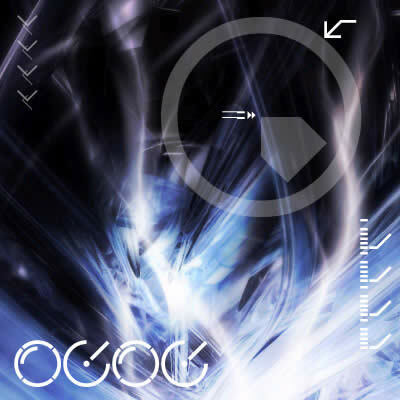
Style Bats autorstwa Vinterstille to darmowy geometryczny font typu dingbats o ostrym, „wczesno-cyfrowym” charakterze. Zestaw opiera się na przejrzystych symbolach – diamentach, chevronach, paskach, schodkowych zygzakach i celownikach w ramkach – powtarzanych w surowym, modułowym rytmie, który przywodzi na myśl połączenie oznaczeń graficznych, ikon interfejsu i abstrakcyjnych ornamentów.
Ten darmowy font sprawdzi się wszędzie tam, gdzie projekt wymaga kompaktowych akcentów graficznych: w plakatach, oznaczeniach sekcji w magazynach, grafikach albumów, kartach tytułowych, projektach opakowań czy prostych nagłówkach stron www. Dzięki temu, że motywy są oszczędne i przypominają wzory, font świetnie sprawdza się w roli obramowań, separatorów, wypunktowań i krótkich znaków graficznych, gdzie zaledwie kilka symboli wystarczy, by przekazać cały zamysł wizualny.
Ostatnio dostrzeżony na okładce albumu Fortune Chrisa Browna.
A little (neatly trimmed) spice for those abstract designs&